设计天城体样式
设计一个新的原创的天城体样式遵循的流程非常类似设计新的原创的拉丁文的流程。从自由字体的自由中能够获得的独特的好处是你可以为字体的初创者从没相处的新目的修改并重用它们–例如设计一个天城体并改造一个已有的拉丁字体来解决它。
天城体字形
天城体包含这些不同类型的字形:
- 辅音(36)
- 独立的元音(28)
- 元音 maatras
- 字距
- 天城体数字(10)
- 拉丁数字(新的或者或者将已有的调整到与天城文字相适应)
- nukta 组合
- 半形式
- 连接(独特的连字字形)
- 不同长度的“I”元音 maatras
- 天城体标点符号
- 拉丁标点符号(新的或者调整已有的)
- 拉丁字母
咨询(天城体 Unicode 页面)和(微软天城体 OpenType 字体开发页面)来学习更多关于这些字形和印度语形状引擎如何工作的内容。
写书法或者与此接近学习字帖来学习书写字母如何工作是有帮助的,这样你会明白什么字母在结构上应该与什么其他字母相似。这些 Aksharaya 的天城体书法字帖中的2页可以用作笔的角度和字母比例的参考。
首先做什么
在设计一个天城体和拉丁字体样式时,以在天城体旁边绘制拉丁文字开始是重要的。最早一步是设计“关键”字形,以此通过基础形状和间距(这在拉丁文中可能是‘adhesion’或者‘videospan’)来建立字体样式的个性。进程早期设计最低和最高的“高度极值”。
你将会需要大量的元音标记来开始质地和缩放的测试。
印度理工大学孟买分校的字体排印教授 Girish Dalvi 博士在他的博士论文中写到,
通过这一研究的结果我们可以推断出 10 个字母 अ इ ए ख त भ द ध थ ष 可以捕获几乎所有的剩余天城体字母的正式属性。在这些字母中,字母 अ इ ख भ द ध ष 定义了大多数字母的特性,是最具决定性的。因此我们认为通过首先设计这些字母,天城体设计的流程可以为学生和字体设计师简化,剩下的字母可以通过这些衍生出来。
Erin McLaughlin 建议将这些字形作为一个初始连字:पाव + किमीनुफू + भरसगदह + र्मों ड्डू (height extremes) + यथधआछड … 连续字符集合并建议关注“Au”元音标记+reph+anusvara 连字!这里的 Ma 是为了后继。
字形的高度极值允许你确定竖直度量值和如何缩放两个书写系统来共同工作。Adobe 发布了非常大的字体家族覆盖各种不同的正字法。它们根据共享的一般比例分成不同的家族;Myriad Pro 包含 Latin,、Greek 和 Cyrillic,而 Hebrew 与 Arabic 设计打包成分来的家族,包含在改进的 Latin 中。
下面是 Myriad Pro Latin 和 Myriad Arabic 并排:
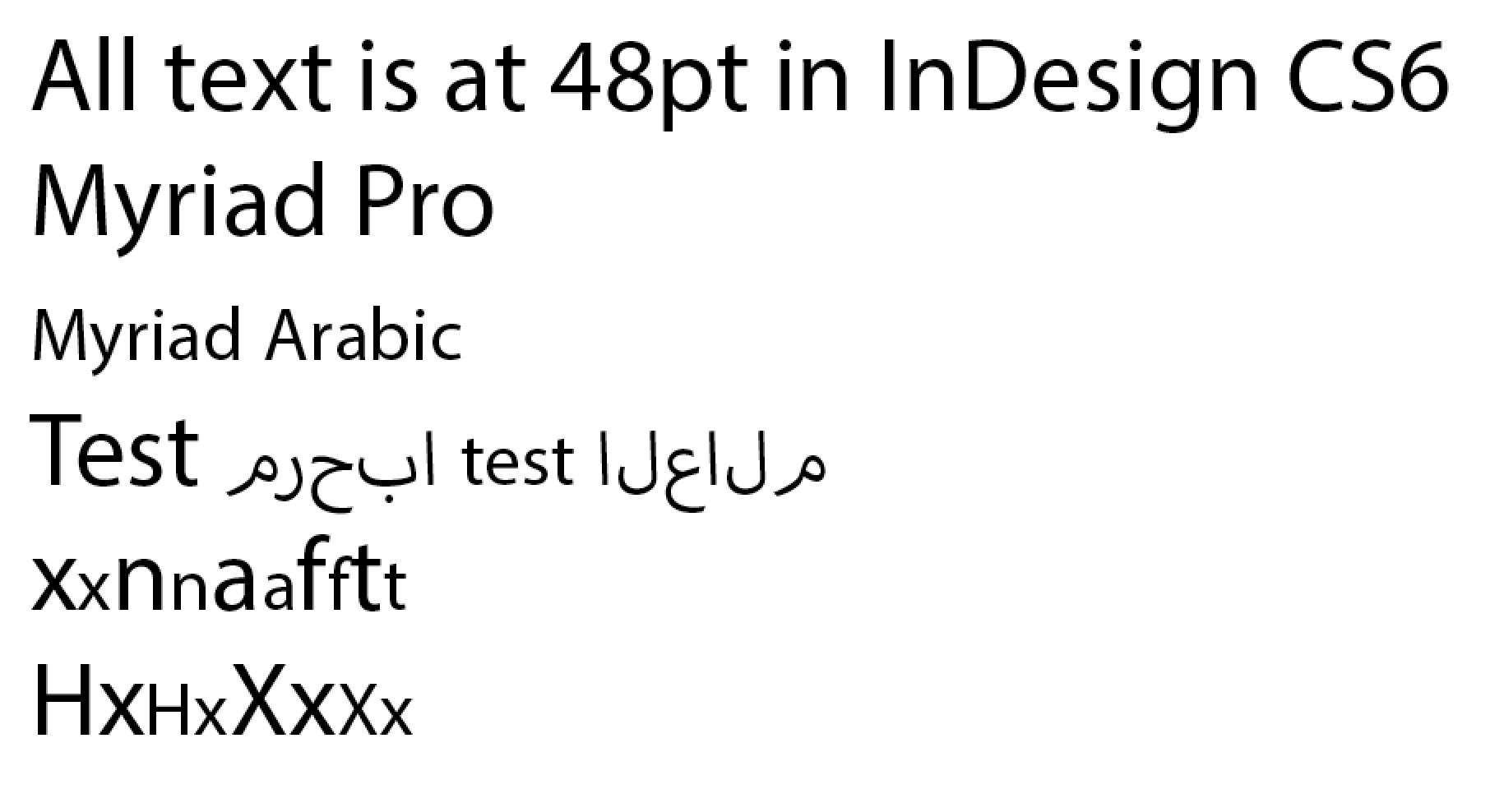
(认出 Adobe 的整洁的选择:Myriad Arabic 的大写高度是 Myriad Pro Latin 的 x 高度)
需要注意的是在 Lohit 字符集中,最低的字形是形式,意味着靠下的字符将会下沉到比基线低很多的地方:
待办事项:添加 vattu+U,vattu+Uu,U,Uu和 subscript V(用于合词)的图片
(Vattu 是底基线样式的 reph。详情参见微软术语页面)
理想地,这些应该堆叠在你最低的竖直堆叠结合以下,就像左边的例子(Lohit 并不完全竖直适应,在右边)
间距方法
设计拉丁字体有代表性地涉及了一系列艰巨字符串像这样:
HHxHOHOxOO
nnXnonoXoo
其中 X 代表了你关注间距的字母,概念是看这个字母挨着有点平的字符和圆的字符。
Pa 与 Va 或 Da 是天城体相等的:
पपXपवपवXवव
पपXपदपदXदद
当刚刚开始一个项目的时候,从使用 Pa 完全填充一个页面开始,以此得到笔画粗细、对立面大小和间距的正确平衡。
पपपपपपपपपपपपप
一旦 Pa 有了正确的“color”,你可以开始添加其他基本常见的字符:
पपपवपपपपपवपववपपव ()va,随机化的)
पपपापपपपापपाप (Aa maatra,岁计划的)
पपपदपपपपपदपददपपद (da,随机化的)
然后你可以开始使用上面的间距字符串来添加新的字形:
पपरपदपदरदद
पपकपदपदकदद
पपलपदपदलदद
पपपीपदपदपीदद
诸如此类!
你将希望在一个像那样长的列表中看看这些,这样你可以在屏幕或打印介质上向下滚动时一个一个地比较字形。做竖直检查比只是长的一行连续文本更有效。原因是:
当你在竖直列中看间距字符串时,你可以很容易地比较当前字符到上下行之间的间距。按同样的方式,你可以容易地从坏地设置完全调整的文本中识别出“rivers”,如果你比较剩下的间距字符串,那么可以容易地在间距上看到白色间隙或者暗点。
上面的间距字符串允许你比较非常不同的形状,这样间距甚至更加贯穿(而不是所有太松或太紧的圆的字符)。
中间的四个字形 Pa/Da/Pa/Da 允许你将比较字符与两个三字符集合相比较,也就是 Pa/Da/Pa 或者 Da/Pa/Da。
在对一些元音和辅音绘制和调整间距后,你将能够只使用这些字母做出数量有限的词并开始用实际文本测试你的设计。
作品分解结构
在任何一个字体样式设计项目中,描绘出一个作品分解结构是好主意。
对于一些非常熟悉的人来说,有可能在大约 4-6 个月内设计出天城体样式的初始的细体和粗体。
这里有一个经验丰富的设计者在设计有些简单的“sans”时,制作 9 种不同粗细、直立和倾斜的插值替换的字体家族的时间表:
| Week | Goal | Glyphs |
| 1 | Establish design in 7-10 key glyphs | 10 |
| 2 | Refine, design tallest glyphs, match heights and weights to Latin in Regular & Bold, test screen rendering with ttfautohint | 20 |
| 3 | Refine proportions with native reader feedback | 40 |
| 4 | Get native reader feedback, refine and add more conjuncts | 100 |
| 5 | Get native reader feedback, refine and add more conjuncts | 200 |
| 6 | Get native reader feedback, refine and add more conjuncts | 300 |
| 7 | Get native reader feedback, refine and add more conjuncts | 400 |
| 8 | Get native reader feedback, refine and add more conjuncts | 500 |
| 9 | Get native reader feedback, refine and add more conjuncts | 600 |
| 10 | Get native reader feedback, refine and add more conjuncts | 700 |
| 11 | Get native reader feedback, refine and add more conjuncts | 800 |
| 12 | Get native reader feedback, refine and add more conjuncts | 900 |
| 13 | Derive Bold | 1,800 |
| 14 | Refinements, Kerning, testing with native reader feedback | 1,800 |
| 15 | Extrapolation and clean-up of Thin and Black weights, generation and clean-up of slanted styles | 3,600 |
| 16 | Interpolated styles refinement | 3,600 |
| 17 | General refinement of spacing, kerning & testing in all styles | 3,600 |
| 18 | Finalisation | 3,600 |
简介
从哪里寻找灵感和创意
在 http://indiantypefoundry.com Google Fonts 发布的网站查看天城体,来找到字体形状变化的灵感。
另一个好的地方是搜索印地语“e-paper”电子报网站来看实际使用字体的广告通常有更多的字体多样性。http://epaper.jagran.com 是一个流通非常广泛的印度电子报纸。
Flickr也是一个形象化创意的好的来源:
历史资源
得到 H. M. Lambert 编写的由牛津大学出版社于 1953 年出版的 Introduction to the Devanagari Script 和 B. S. Naik 编写的孟买语言理事会 1971 年出版的 Typography of Devanagari(3 卷)的副本。
除了那些,还有至少两种欧洲 19 世纪字体的一般来源值得一看:英国和德国(主要是莱比锡)的字体样式。这些字体更多地用来设置梵文字文本而非印度文本。
同时也尝试从印度字体铸造中找到 19 世纪和 20 世纪的文本字体样式的例子。像你期望的那样,它们明显很少欧化。从 19 世纪起在欧洲学院 梵文字体中有一些靠不住的东西,它们看起来根本不存在于 20 世纪的印度的排印中。这些印度来源可能更难从西方图书馆中找到,但是可能 Erin McLaughlin 更加领先。例如 Matthew Carter 的 19 世纪 70 年代的天城体 Linotype 排字机是基于 Nirnaya Sagar 公司的字体样式。它们的字体和孟买字体公司的字体应该可以在一些西方大学或者国家图书馆中找到。我也推荐查找 Monotype 的天城体和 LinoType 天城体(1970 年代版和 1980/90 年代版,而非指示同名的原始的 1935 版)。
Pablo Impallari 的天城体测试页面 (以及 Github 上的源码)提供了一些已经制作好的测试布局,你可以拖动你的 OTF 或者 TTF 字体到页面上来加载它。
Pooja Saxena 的字体工具(以及 Github 上的源码)来生成字母连接的测试文本。
Adhesion 天城体文本是 Miguel Sousa 构建的用来制造只包含可能使用你已经绘制的字形来书写的单词的假文本 的工具的一个特殊版本。插入你已经绘制的字形(अआईईउऊ 等),将会诞生一些你用于证明的示例单词。
Huerta Tipografica 的 Devanaguide 是一个开源工具,用来看和比较不同的天城体。它也允许你打字并同时在所有字体上预览。Devanaguide 也包含了一个天城体词表,对测试文本设计有帮助。